Font script tipis adalah salah satu font terbaik untuk merepresentasikan brand yang memiliki karakter lembut dan elegan. Gaya huruf tampil seperti tulisan tangan yang halus dan ringan, yang mana menciptakan kesan personal, anggun, dan penuh kelembutan. Desain logo script tipis dalam berbagai brand dapat berkesan manis, halus, dan profesional, termasuk juga brand feminim dan artistik.
Pemilihan font tipis dengan gaya huruf bersambung tidak hanya sekedar menciptakan kesan elegan dan feminim, tetapi juga berguna untuk membangun citra lembut dan estetik. Tampilan yang lembut dan elegan, membuat brand ini sering digunakan untuk mewakili identitas brand kecantikan dan fashion. Namun tentunya, font script tipis dalam digunakan dalam berbagai jenis brand lain.
Kesan Font Script Tipis dalam Berbagai Jenis Logo
Desain logo yang memiliki gaya font tulisan tangan umumnya akan tampil personal dan berkesan lebih ramah. Jika menggunakan style font tipis, terkadang logo akan tampil mewah terutama dengan style logo minimalis. Penting untuk memilih style font script tipis dan warna yang relevan agar sesuai karakter brand, seperti beberapa logo ini:
Logo Flower Studio Pilates
Desain logo studio pilates ini memiliki kombinasi ikon line art bunga dan perempuan dengan garis tipis. Yang style ikon line art dengan garis tipis akan harmonis dengan font script tipis. Warna merah muda membuat logo pilates studio memiliki citra brand yang:
Lembut dan Tenang: Garis tipis yang halus dan warna pink pastel akan menciptakan kesan brand pilates yang lembut dan halus. Cocok untuk target pasar perempuan yang suka merawat kesehatan tubuh.
Font script tipis dalam logo pilates ini menunjukkan bahwa pilates adalah olahraga yang merawat diri dengan elegan.
Gaya huruf tipis juga menciptakan kesan olahraga pilates yang rileks dan eksklusif.
Logo Fashion Perempuan dan Anak
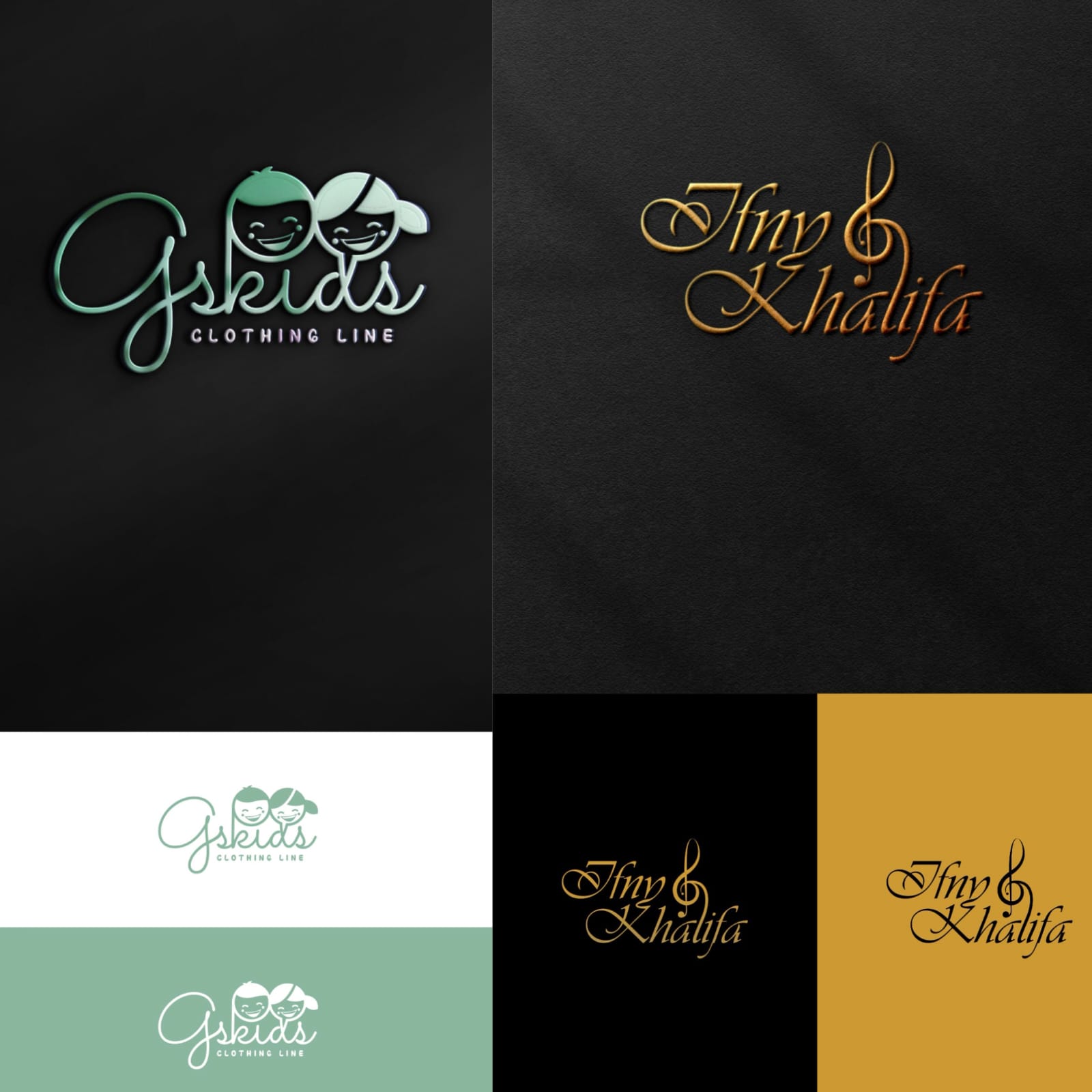
Desain logo fashion untuk perempuan dan anak ini memiliki dua style font yang berbeda karena satunya lebih elegan dan satunya tampil ramah. Gaya huruf script tipis dalam logo fashion memiliki sudut dan ujung yang tajam. Sementara font script tipis dalam logo fashion anak-anak tampil melengkung sehingga berkesan ramah.
Untuk fashion perempuan, font script tipis menciptakan kesan logo elegan, modern, feminim, dan anggun.
Untuk brand anak-anak, gaya font tipis yang melengkung akan memberi nuansa manis, imut, dan ramah.
Desain logo minimalis dengan font script tipis akan membuat logo terlihat halus, bersih, dan premium, cocok untuk membuat fashion memiliki citra high-end.
Logo Brand Gula
Style font script tipis yang seringkali menciptakan kesan elegan, cocok juga untuk desain brand makanan. Desain logo untuk bisnis gula aren ini memiliki style font script tipis yang memiliki gaya huruf halus dan bersih. Brand gula aren ini memiliki gaya font script dengan warna hijau, dan dekorasi daun buah aren.
Font tipis dalam brand gula aren memberi kesan manis, lembut, dan merepresentasikan identitas brand gula dengan baik. Gaya font ini cocok untuk brand gula homemade, dessert lokal, atau bakery rumahan.
Font script dalam logo gula akan menambah kesan handmade, gaya huruf tulisan tangan akan menciptakan kesan produk gula yang dibuat dengan penuh kasih dan detail.
Style font script tipis yang dipadukan dengan warna hijau lembut membuat desain logo akan lebih menyenangkan dan berkesan premium.
Logo Fotografi
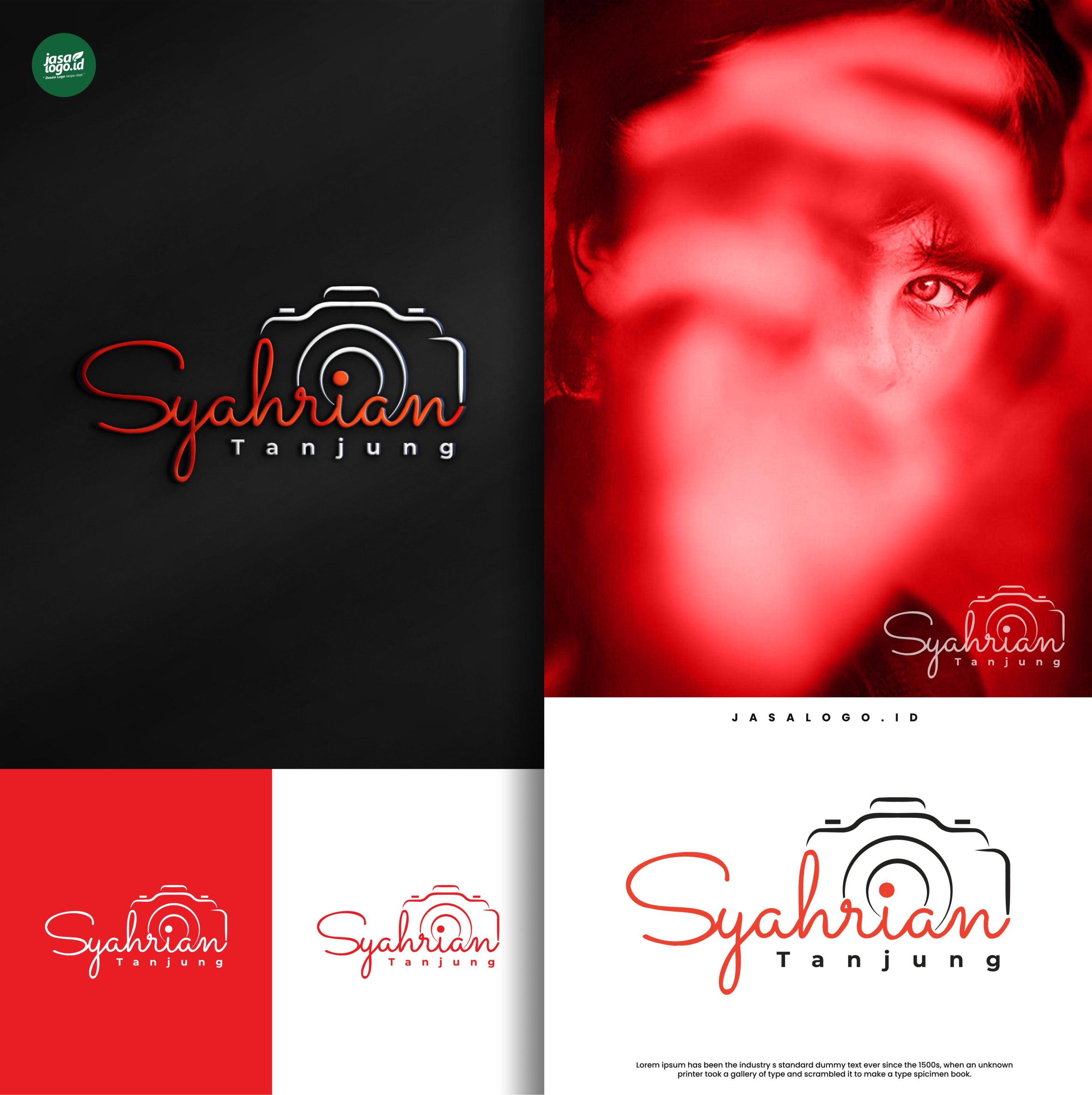
Desain logo untuk bisnis fotografi ini memiliki font script tipis dengan gaya huruf bersambung dan halus. Style font tipis yang halus dan bersih memudahkan logo fotografi untuk dibaca dan menciptakan kesan profesional. Sudut huruf script ini melengkung tidak tajam sehingga menciptakan ramah dan menyenangkan.
Pada fotografi, font script tipis akan menunjukkan gaya fotografi yang artistik, lembut, dan personal.
Font ini cocok untuk fotografer yang fokus pada wedding, newborn, atau fine art fotografi.
Penggunaan gaya font elegan ini akan menciptakan kesan jika foto bukan sekedar dokumentasi tetapi ekspresi estetik dan emosional.
Mengapa Font Script Tipis Cocok untuk Logo Brand Feminim dan Artistik?
Font script tipis memiliki gaya huruf latin dengan garis yang halus, bersih, dan memiliki kesan elegan. Terkadang ada yang memiliki gaya huruf lancip, tajam, tetapi juga ada yang melengkung sehingga tampil ramah. Tampilan font yang elegan dan feminim membuat font script tipis dapat digunakan untuk berbagai brand. Berikut alasan font script tipis cocok untuk brand feminim dan artistik:
Mewakili Keanggunan dan Feminitas
Font script tipis memiliki garis-garis halus yang tampak mengalir dan lentur, membuatnya sering diasosiasikan dengan feminitas, kelembutan, dan keindahan. Untuk itu font ini cocok untuk menyasar brand dengan target pasar perempuan. Style font elegan dan feminim akan relevan untuk digunakan dalam logo:
- Brand fashion wanita seperti butik dan perhiasan
- Logo studio pilates atau yoga.
Menonjolkan Sentuhan Artistik dan Personal
Gaya font script yang memiliki style huruf tipis ini menyerupai tulisan tangan yang elegan, sehingga menciptakan kesan brand dibuat oleh tangan dengan penuh cinta. Untuk itu brand homemade, handmade, atau produk kreatif sering menggunakan gaya font script tipis. Style font ini cocok mewakili brand yang memiliki nuansa artistik, kreatif, atau handmade seperti:
- Logo fotografer pernikahan atau newborn
- Brand kerajinan tangan.
Menciptakan Identitas yang Lembut dan Ramah
Tidak semua brand harus memiliki kesan kuat dan bold, sehingga tidak harus memiliki font tebal dan tegas seperti sans serif. Beberapa brand akan lebih cocok untuk memiliki visual ramah, manis, dan mudah dijangkau, yang cocok dengan font script tipis yang mengalir dan lembut. Font script tipis yang mengalir seperti tulisan tangan yang berkesan ramah cocok untuk brand seperti:
- Brand makanan manis atau bakery rumahan
- Logo produk skincare alami atau organik.
Cocok untuk Segmen Perempuan dan Anak-anak
Style font script tidak hanya elegan tetapi juga bisa tampil ramah sehingga cocok untuk segmen pasar brand perempuan dan anak-anak. Dalam brand anak-anak dan perempuan akan harmonis jika font script tipis dikombinasikan dengan warna pastel. Kombinasi akan menciptakan kesan lembut dan menyenangkan, serta tampil elegan dan ceria.
- Brand hijab
- Logo fashion anak-anak
Baca juga: Rekomendasi Font Modern untuk Jenis Brand Berbeda
Psikologi Warna dalam Font Script Tipis
Jika umumnya font script yang tipis dengan garis halus yang mengalir akan tampil elegan dan feminim. Namun jika dikombinasikan dengan warna tertentu dapat menciptakan yang berbeda. Kombinasi font script tipis dengan warna tertentu akan menciptakan kesan seperti:
Script Tipis dan Dusty Pink: Kombinasi banyak ditemui dalam logo fashion, skincare, dan brand dessert karena menciptakan kesan manis, feminim, dan romantis.
Font Script Tipis dan Emas atau Silver: Logo ini akan cocok untuk mewakili identitas brand perhiasan, brand mewah, dan produk eksklusif karena akan berkesan premium dan mewah.
Script Tipis dan Putih dalam Latar Warna Hitam: Biasanya akan memiliki style logo minimalis dan bersih sehingga menciptakan kesan brand elegan dan dramatis.
Kesimpulan
Visual font script tidak hanya membuat desain logo tampil lebih indah tetapi dapat menghidupkan karakter brand yang ingin tampil lembut, anggun, dan penuh seni. Style font yang elegan ini cocok untuk brand seperti fashion, bakery, pilates, hingga logo makanan. Font script akan tampil lembut dan feminim jika dikombinasikan dengan warna pastel, sementara jika memiliki warna emas akan tampil mewah dan premium.